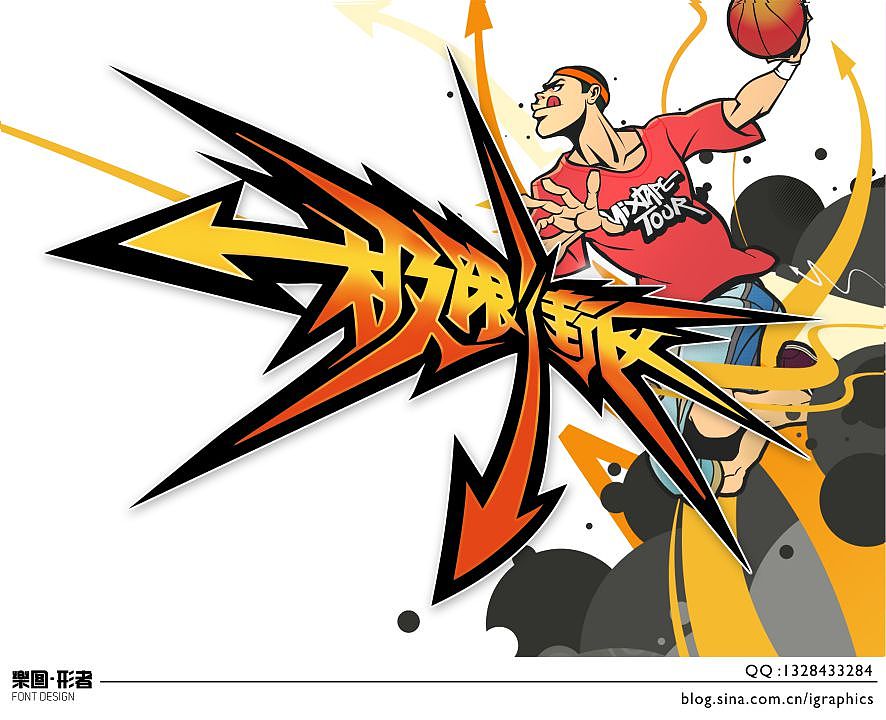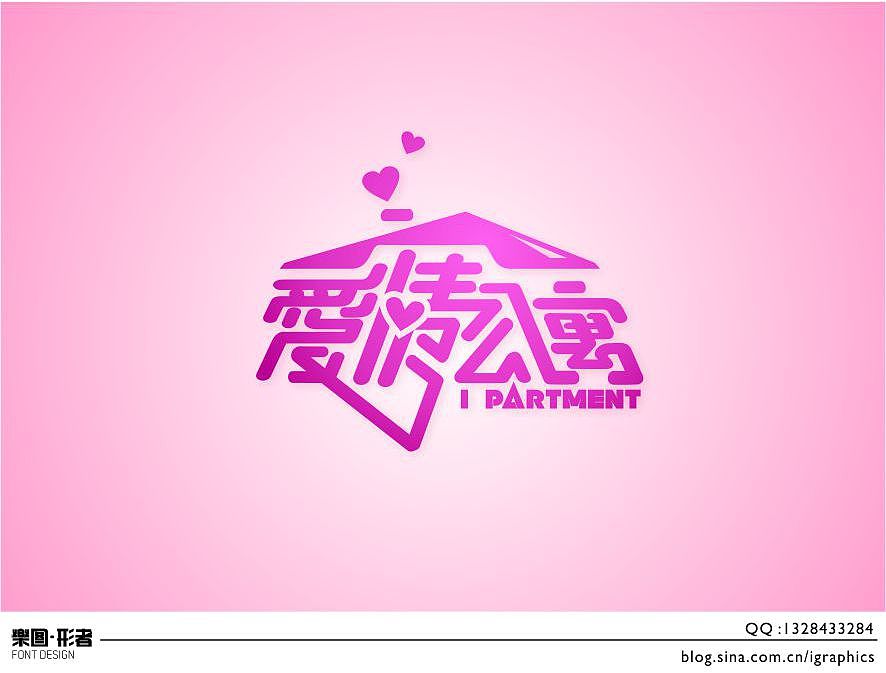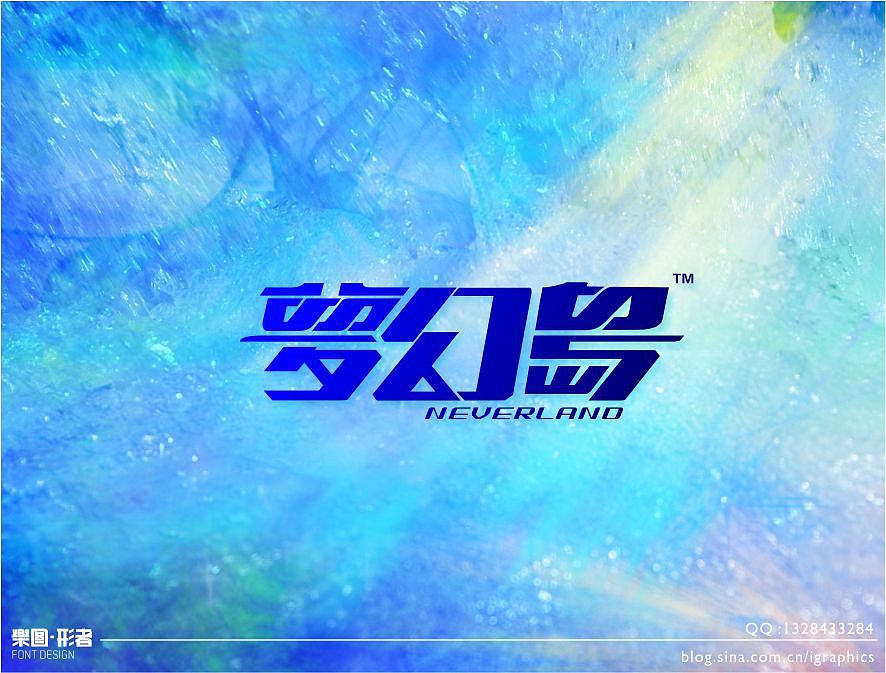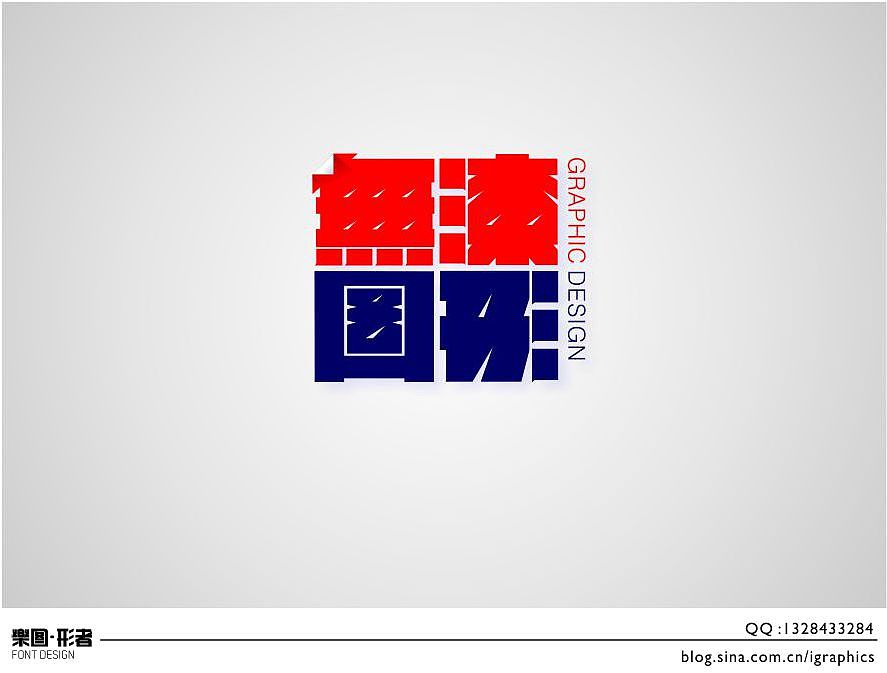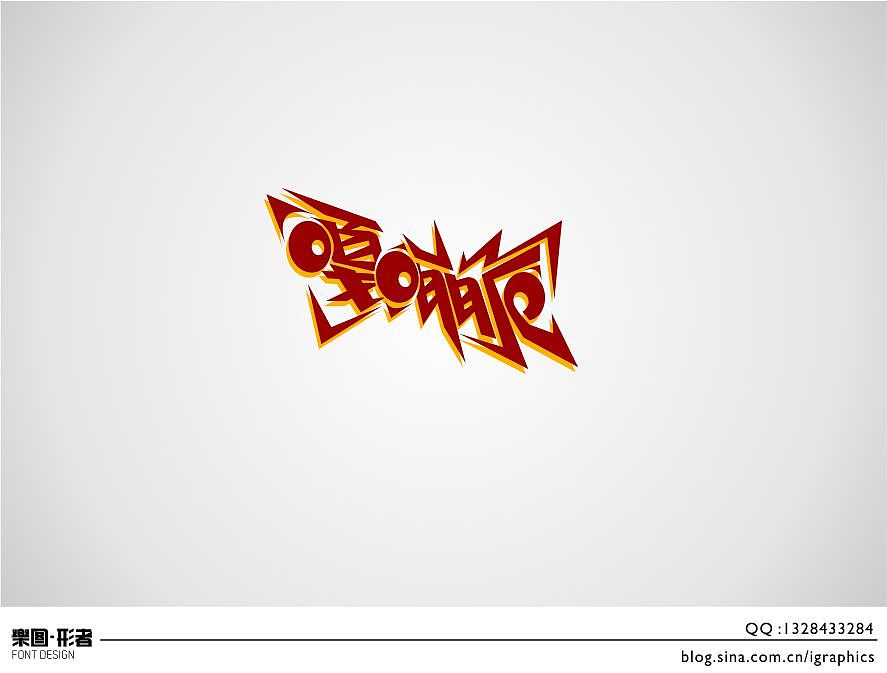
尝试不同风格字体设计
最近一段时间的字体设计,字与形的结合一直穿插在自己的创作中,可以直观的传达字体想要表达的意义;接触各种不同风格的字体设计,总结规律运用在自己的设计中,不断地变换组合,往往有意想不到的效果。
极限街区(背景图片仿街球2)
玩酷子弟
剪秋萝
真诚滋味
爱情公寓
梦幻岛
生日快乐
青春秀
电台音乐私享会
无漆图形
谷香果色
薯+快乐
乐图·形者
时尚素膳坊
天才在左疯子在右
嘎嘣脆
荣华服贵